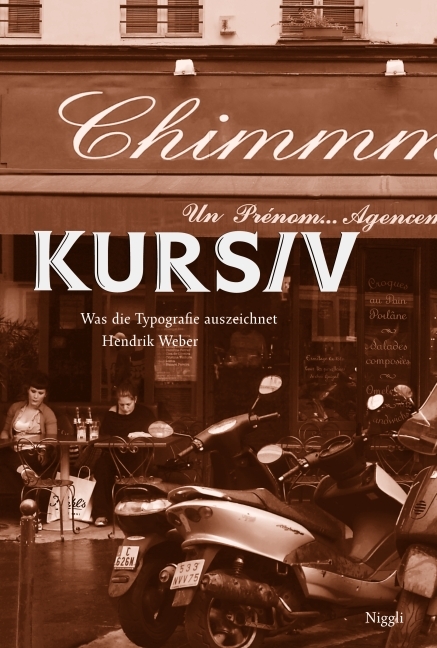
Kursiv. Was Typografie auszeichnet
Spätestens seit der Einführung von Heimcomputern und der damit verbundenen Nutzung von Schreibprogrammen sind kursive Auszeichnungsmethoden für jedermann gängige Praxis.
Kursiv wird durchweg als Auszeichnung geschrieben, gelesen und verstanden. Neben der statisch wirkenden 'aufrechten' Letterform birgt 'kursiv' eine bewegend schöne Eigendynamik, die etwa sinnliche Erfahrungen des Lesens anspricht. Dieses lebendige Charakteristikum, das einst aus der Schreibbewegung resultierte, verliert sich zusehends, wenn Wörter nur noch per Mausklick schräg gestellt werden. Der Übergang von der Handschrift zur digitalen Schrift hat den Autor dazu veranlasst, Gestaltungsmuster kursiver Schriften zusammenzutragen und konkreten Formeigenschaften und Funktionen 'kursiver Natur' nachzugehen. Zudem wird in der Publikation detailliert die historische Entwicklung der Kursiven dargestellt.
Dieses Buch ist die erste ausführliche Abhandlung zu einem Thema, das aufgrund seiner traditionellen Wurzeln auch Nicht-Kennern typografi scher Normen einen interessanten Einblick in das Fachgebiet gewährt - aus dem leidenschaftlichen Blickwinkel heutigen Schriftschaffens.
Kursiv wird durchweg als Auszeichnung geschrieben, gelesen und verstanden. Neben der statisch wirkenden 'aufrechten' Letterform birgt 'kursiv' eine bewegend schöne Eigendynamik, die etwa sinnliche Erfahrungen des Lesens anspricht. Dieses lebendige Charakteristikum, das einst aus der Schreibbewegung resultierte, verliert sich zusehends, wenn Wörter nur noch per Mausklick schräg gestellt werden. Der Übergang von der Handschrift zur digitalen Schrift hat den Autor dazu veranlasst, Gestaltungsmuster kursiver Schriften zusammenzutragen und konkreten Formeigenschaften und Funktionen 'kursiver Natur' nachzugehen. Zudem wird in der Publikation detailliert die historische Entwicklung der Kursiven dargestellt.
Dieses Buch ist die erste ausführliche Abhandlung zu einem Thema, das aufgrund seiner traditionellen Wurzeln auch Nicht-Kennern typografi scher Normen einen interessanten Einblick in das Fachgebiet gewährt - aus dem leidenschaftlichen Blickwinkel heutigen Schriftschaffens.
Hendrik Weber (*1978 in Dresden) begann 2001 in Potsdam sein Studium, das er 2008 an der Hochschule für Grafi k und Buchkunst in Leipzig abschloss. Er besuchte die Fachklasse für Schrift bei Prof. Fred Smeijers. Hendrik Weber lebt in Berlin und arbeitet, referiert und unterrichtet im Bereich Schrift und Typografie in ganz Deutschland.